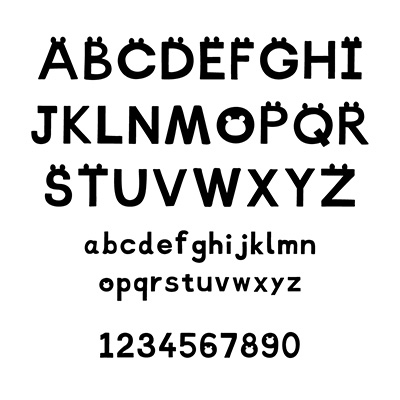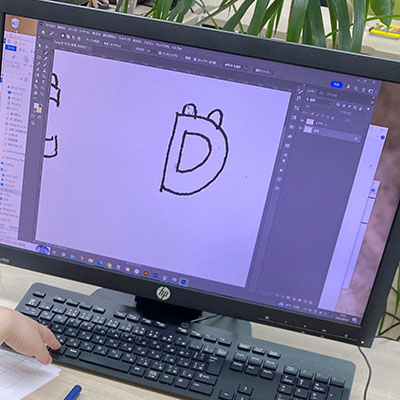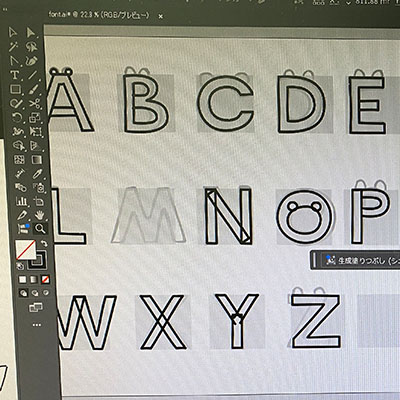
Kumajiフォント
くまがワンポイント
ちょっとした手描き感を出し、やわらかい印象を意識しました。(秋津)
熊のモチーフを取り入れた、インパクトと遊び心のあるフォントです。(秋津)
ひょっこり飛び出たまるい耳がアクセントのフォントです。ところどころにクマが隠れているので探してくださいね。(就労継続支援事業所TED)